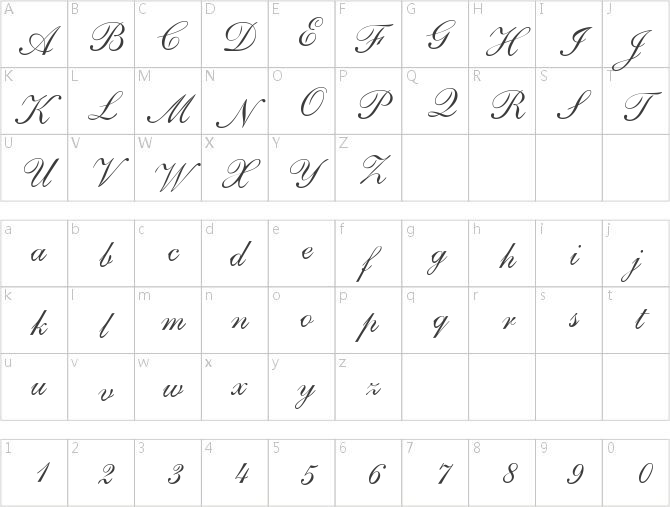
SarahAndanteDB
SarahAndanteDB介紹
SarahAndanteDB字體字庫是一款讓人賞心悅目、百看不厭的英文字體,適合各類廣告和產(chǎn)品包裝設(shè)計(jì)應(yīng)用,字體大小0.07MB,格式為ttf字體,上傳用戶是惠祥博達(dá),作者/版權(quán)方為未知